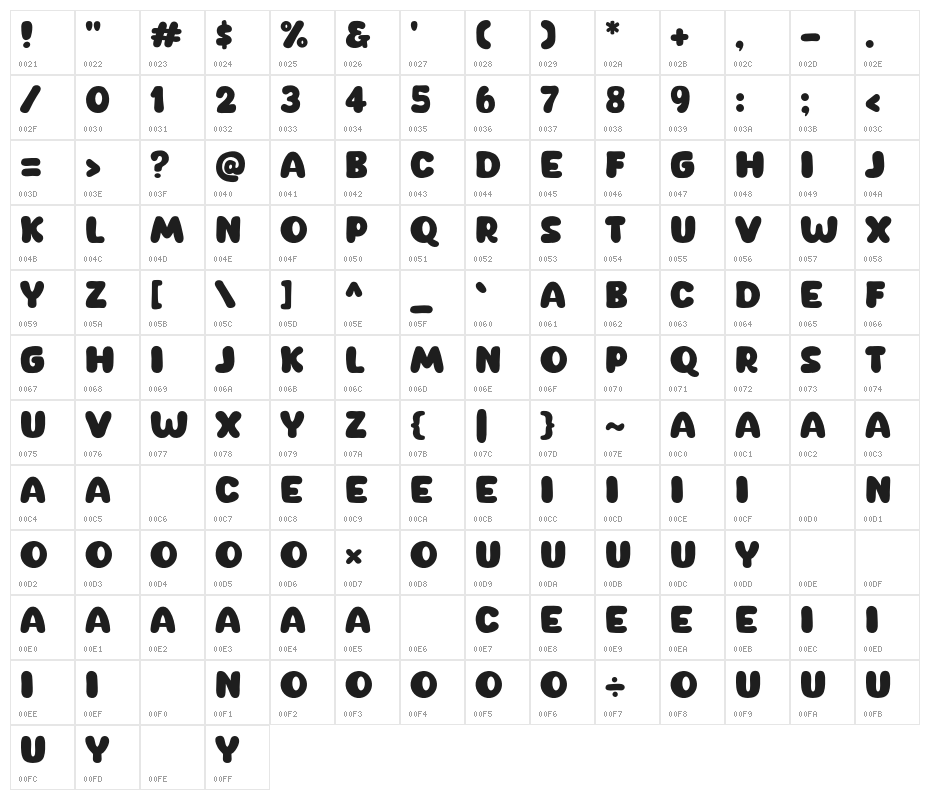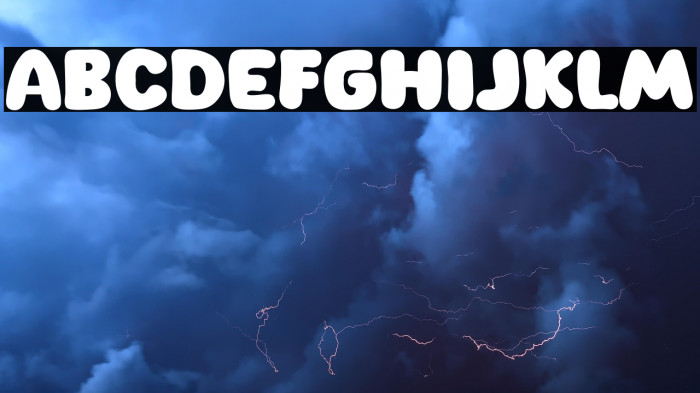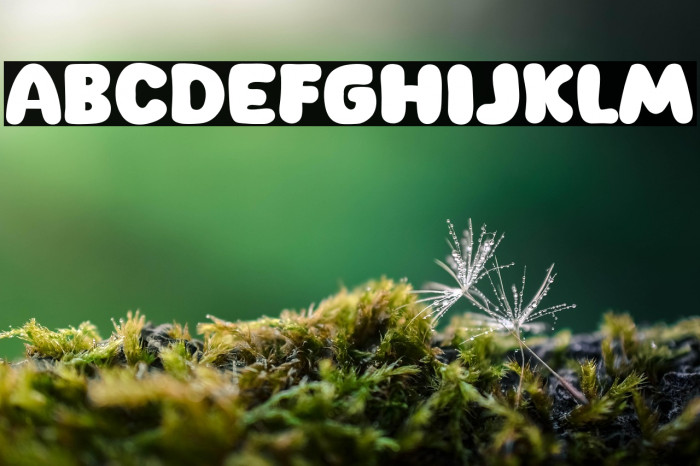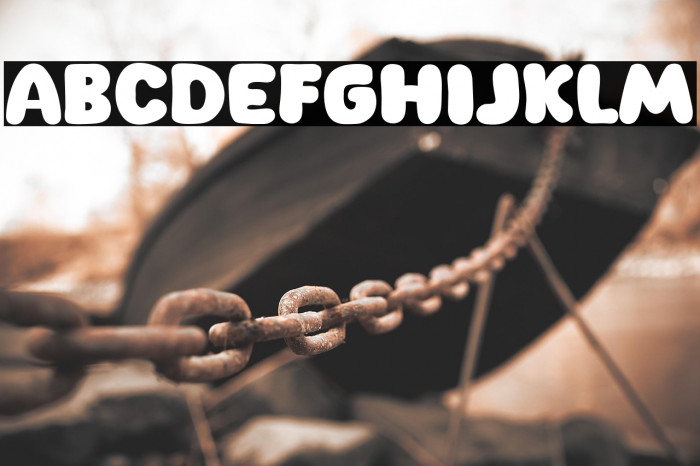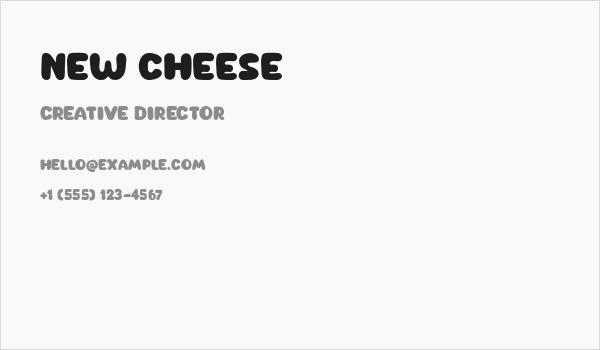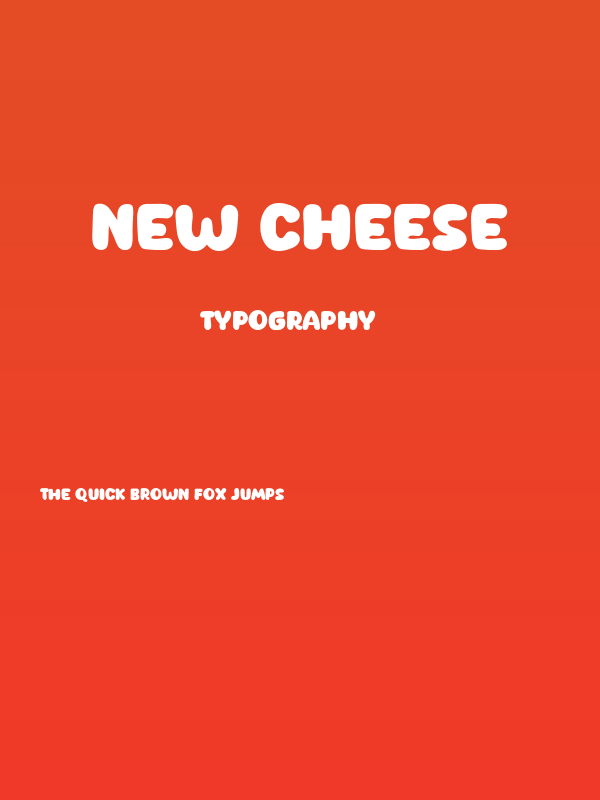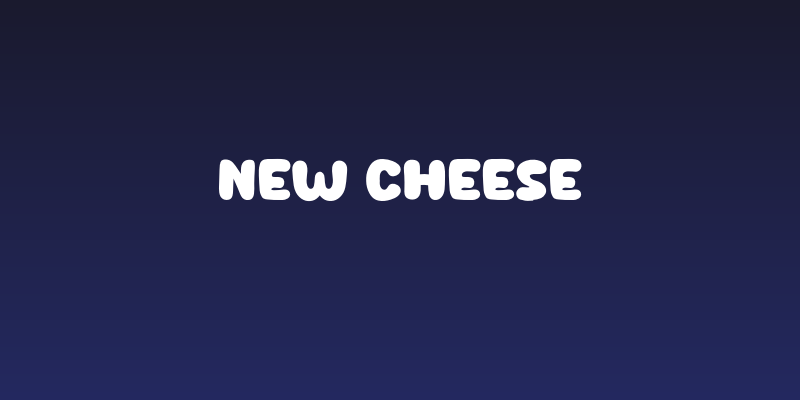
New Cheese Font
| 整体风格 | Playful |
| 推荐项目 | Ideal for children's books, playful branding, party invitations, and any project needing a fun, approachable look. |